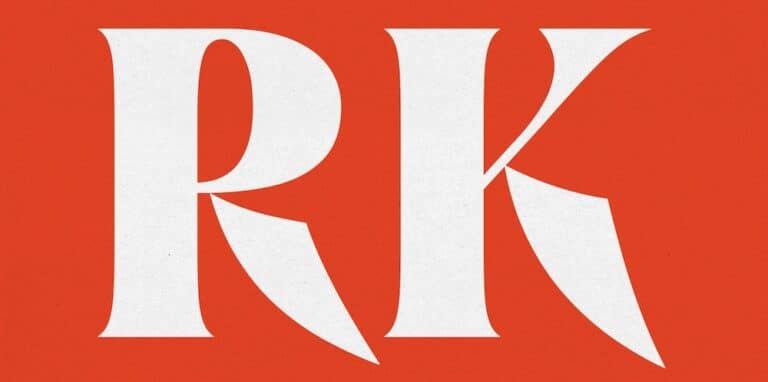
Elegante Serifenschrift Brillante
Für Headline und Text, für Web oder Print – die Schriftfamilie Brillante lässt sich vielfältig einsetzen.
Die sorgfältig gestaltete Schrift Brillante von der Black [Foundry] aus Paris, stellt die Welt der Mode, des Luxus und des Schmucks ins Rampenlicht.  Von den markanten Buchstaben V und W mit ihren unverwechselbaren Zacken bis zu den zarten und zugleich dornigen Lettern K und R verkörpert Brillante Eleganz. Die kurzen Serifen wiederum, ermöglichen enge Abstände und verleihen der Schrift eine moderne und kantige Ausstrahlung.
Die Typedesigner:innen Jérémie Hornus, Solenn Bordeau und Jolana Sýkorová legten Brillante in 15 Schnitten an: Die fünf Strichstärken Thin, Light, Regular, Bold, Black jeweils in den drei Breiten Compressed, Condensed und Normal. Einen Variable Font mit den Achsen Weight und Width gibt es außerdem. Der Preis der Schrift hängt stark von ihrem geplanten Verwendungszweck ab, mehr erfährt man auf der Black [Foundry] Website.